百千鳥フォント
一款独特的字体,兼具手写笔触的温暖与精致的锐利。
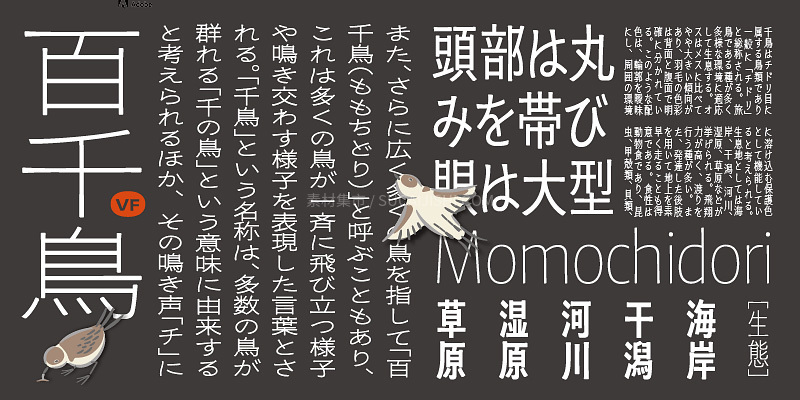
いおゴシックゴールド
这款字体以现代视角重现了凸版印刷的丰盈质感。其沉稳的色调与标题和正文完美融合。
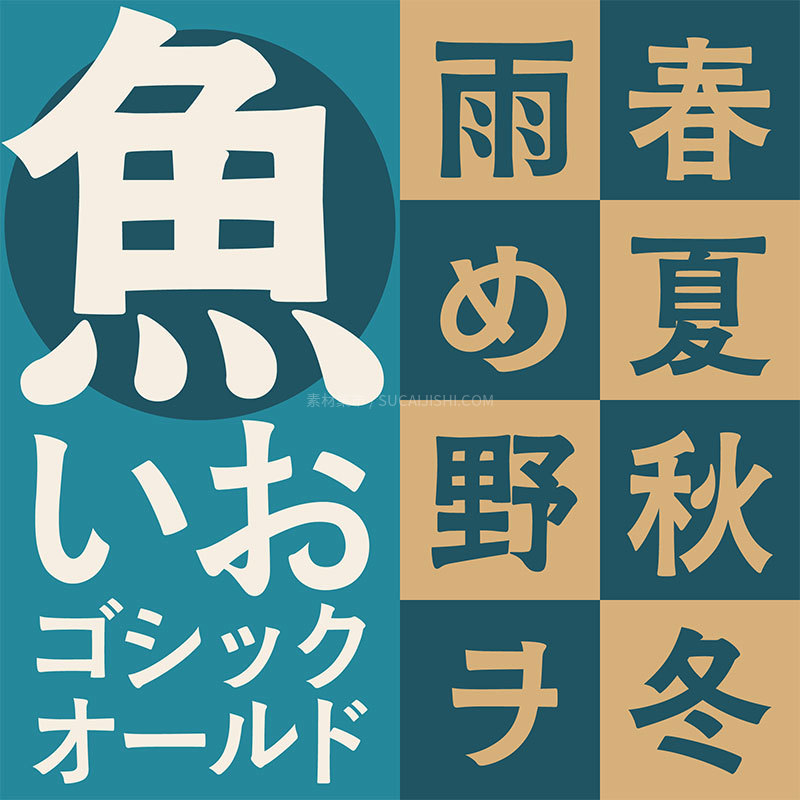
源暎きわみゴ
这款超粗体哥特字体基于“ Dela Gothic ”,并用原始字形替换了假名和字母数字字符。它包含约 7,800 个汉字。
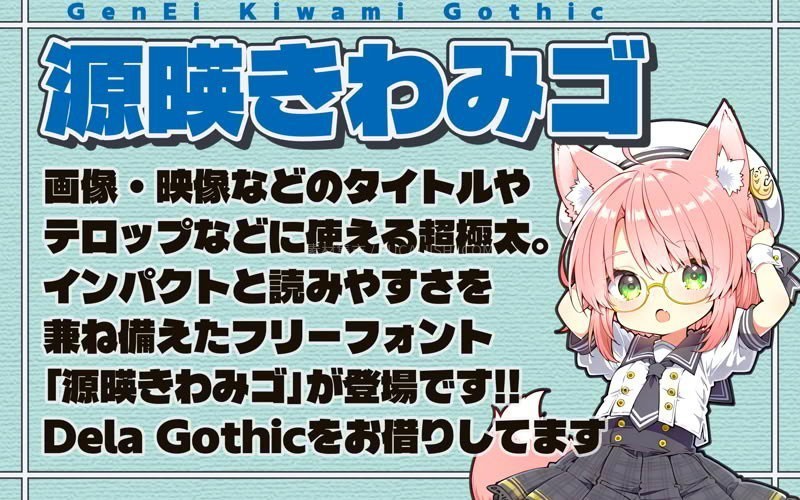
ノエリーフ
这是一款柔和的手写字体,支持平假名、片假名、英语、数字和符号。用钢笔在纸上书写的字符会被扫描,并逐个字符地仔细转换成数字字体。
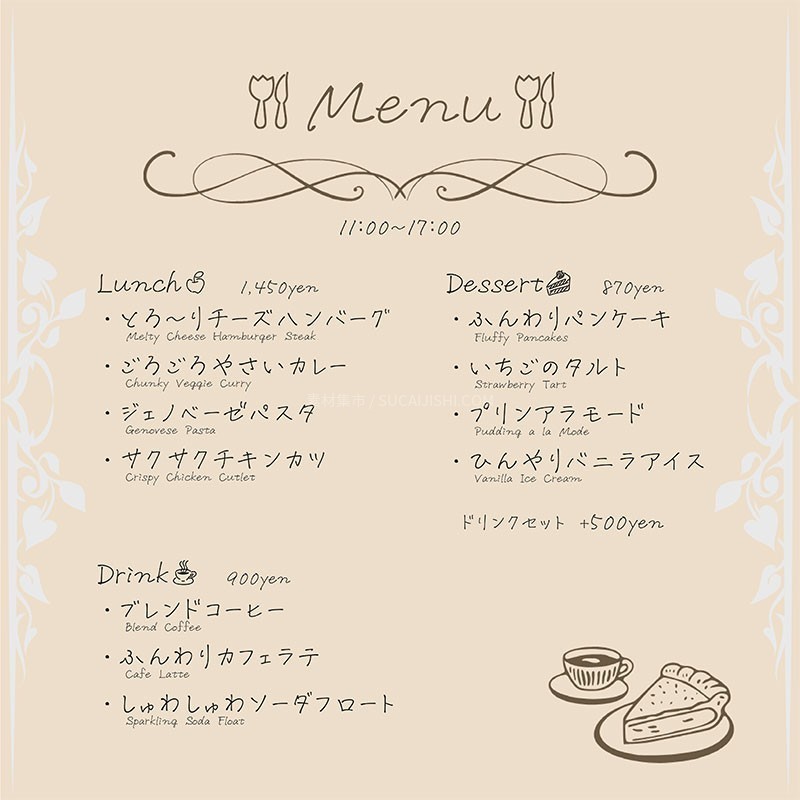
機械彫刻用標準書体フォント
这款免费的日语字体专为雕刻而设计,重现了复古警示牌和奖杯牌匾上常见的字符。除了平假名、片假名、字母数字字符和符号外,它还包含 600 多个常用汉字。12款免费商用日文字体合集12款免费商用日文字体合集
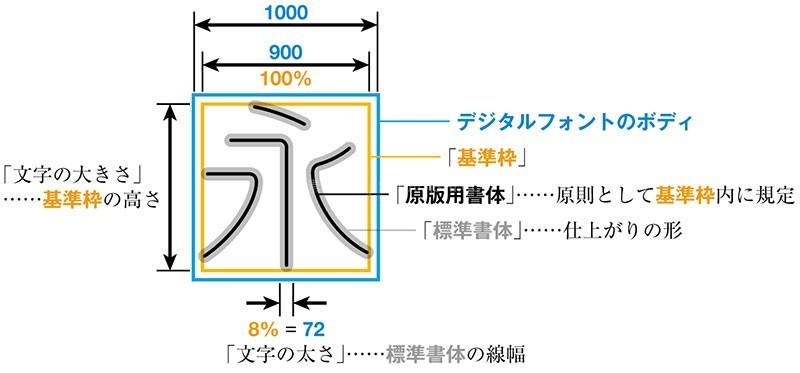
夜すがら手書きフォント
这种手写字体具有独特的人性化感觉,是夜复一夜在 iPad 上手工制作的。
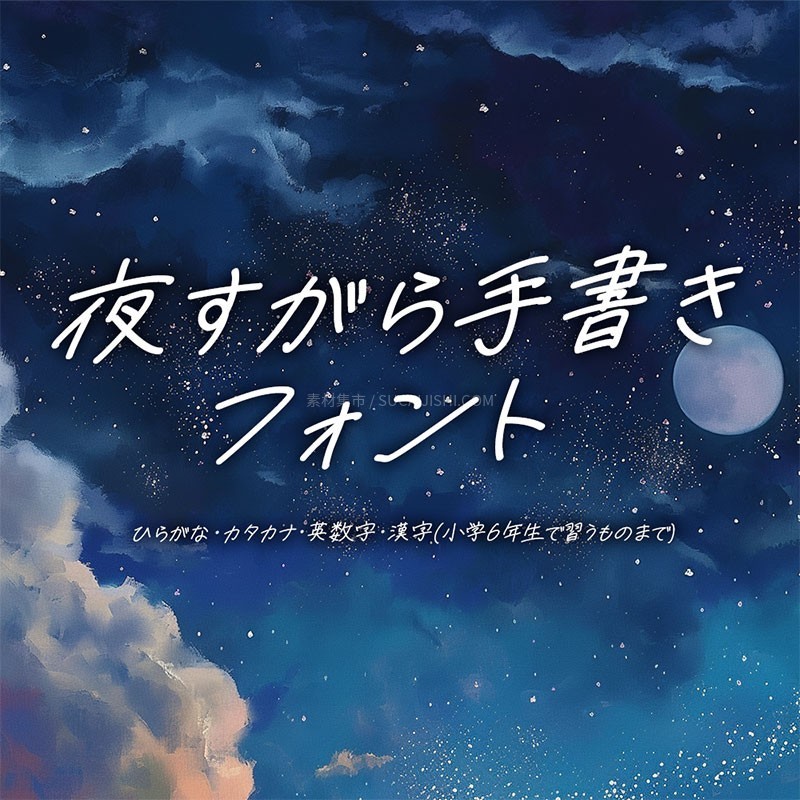
夜の手書きフォント Yorutegaki
这款手写字体虽然不算特别好,但个性鲜明。它包含平假名、片假名、字母数字、符号以及一些汉字。字体粗细有三种,从细到粗。
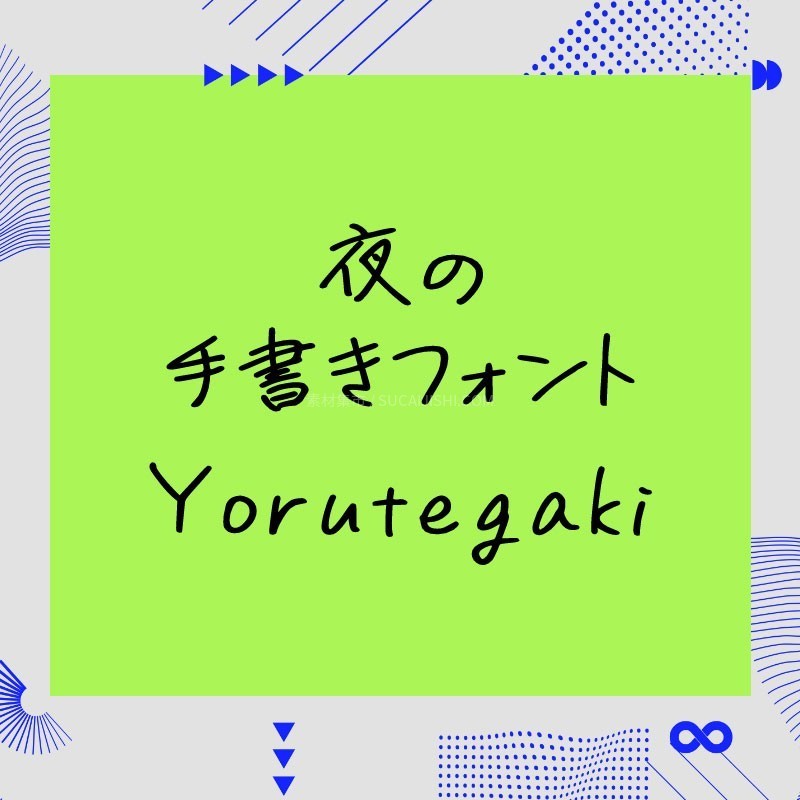
山びこやま フリー版
一款纵向延伸、柔和清新的日文字体。包含平假名、片假名、数字和符号。零售版包含 1,026 个教育用汉字。
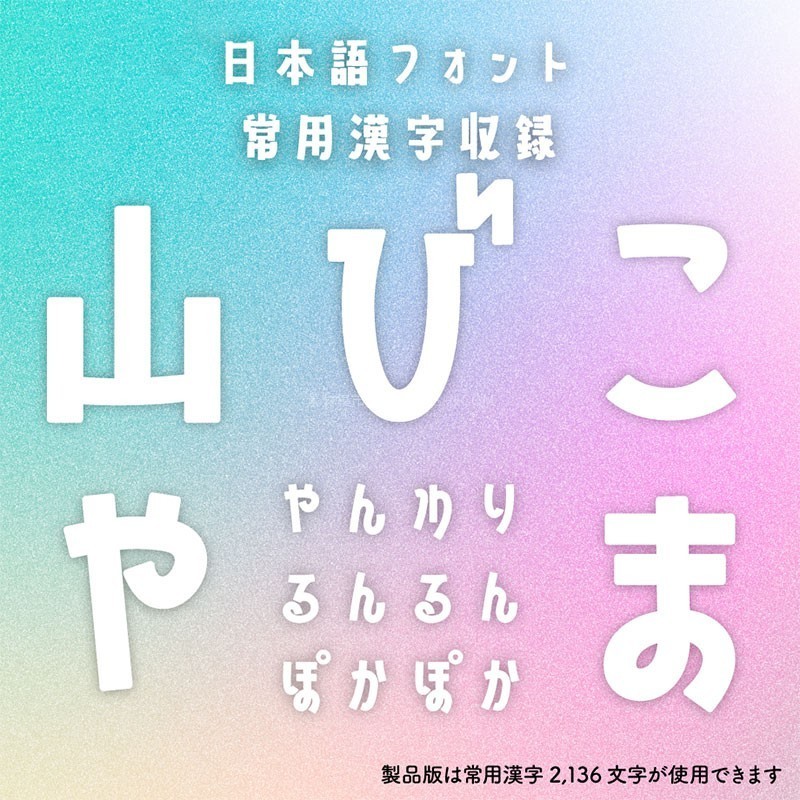
あるぺんフォントフリー版
这款字体是通过数字化手写字符创建的。免费版包含约 1,700 个字符(包括教育用汉字),而完整版则包含 7,140 个字符。
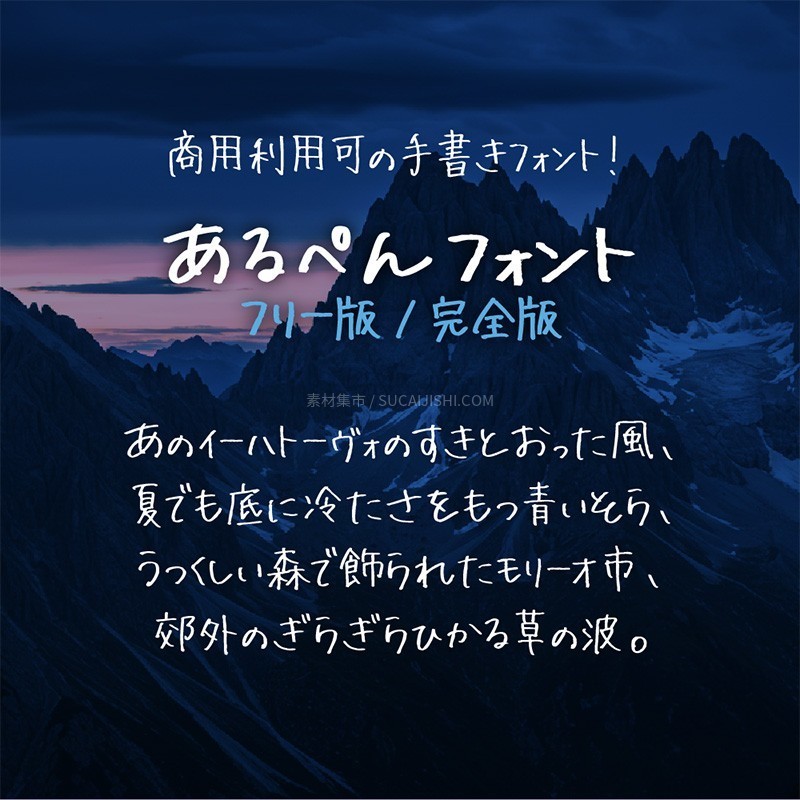
風と大地の太ゴシック無料版
一款格外粗体的哥特式字体,令人联想起风的力量和大地的磅礴气势。其极具冲击力的设计,完美适用于标题和标题。
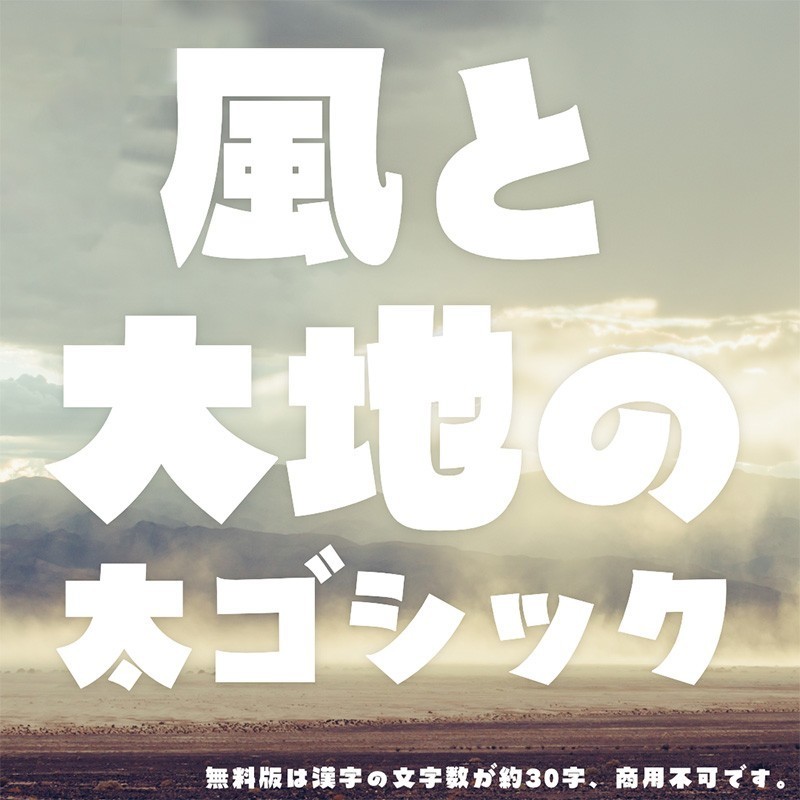
みぎかたあがり
这是一款手写字体,笔触粗糙,略带潦草感,略带上倾。
築豊初号明朝OFL│見出し向け明朝体
一种老式的明朝字体,适用于标题、标题和其他需要突出的地方。它遵循筑地圣语的传统,其特点是基于“月读圣语标题假名”的刷写假名以及坚实、结构良好的笔画。